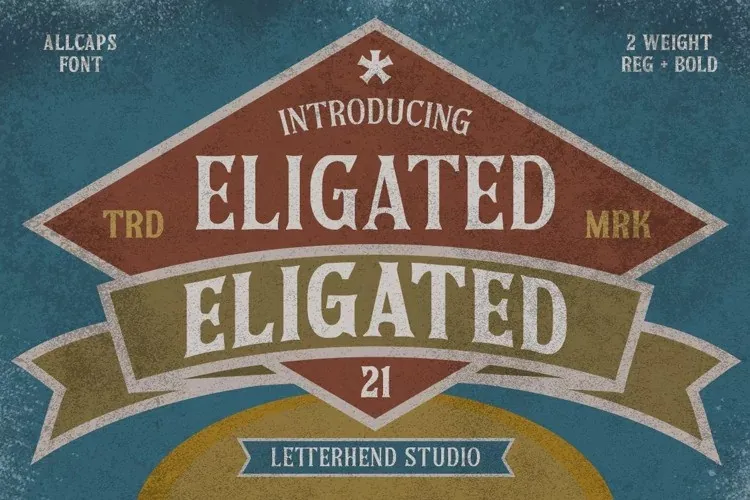
A fonte Eligated é uma opção para quem busca um design elegante e sofisticado que remete à década dos anos 60 e 70. Desenvolvida pelo Letterhend Studio, esta serif typeface traz um aspecto retro-futurista perfeito para aplicação em logotipos, headlines, sinalizações e outros tipos formais como convites, selos, logos, magazines, livros, cartões de cumprimentos ou cartas de casamento, embalagens, moda, maquiagem, estoque, novelas, selos, ou qualquer propósito de marketing. Inspirada nas plaquettes daquela era, Eligated oferece um charme único que fará seu design soar mais sofisticado e autêntico, sem perder a elegância tradicional das serif typefaces. Seja para trabalhos profissionais ou artísticos, Eligated está pronta para dar vida ao seu projeto de forma única.